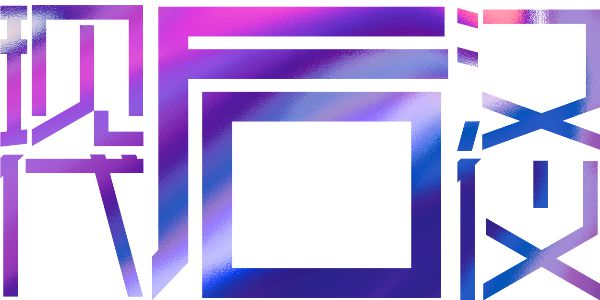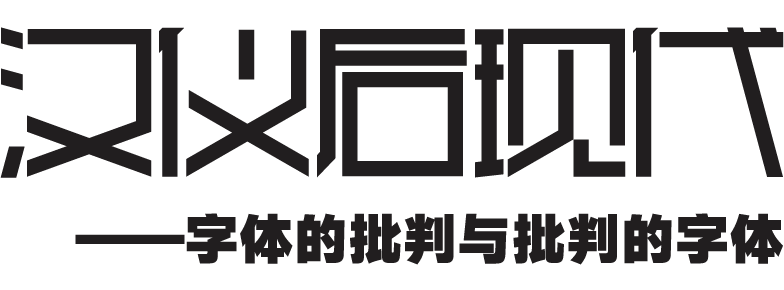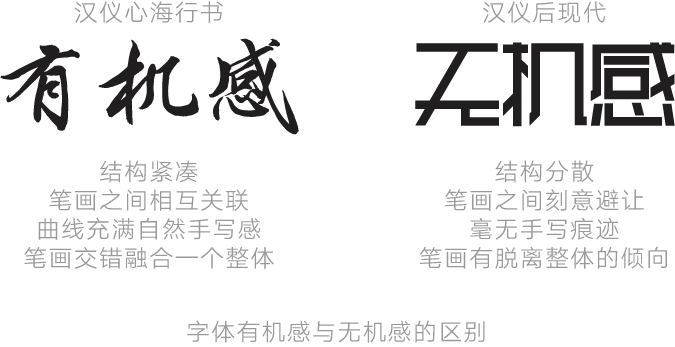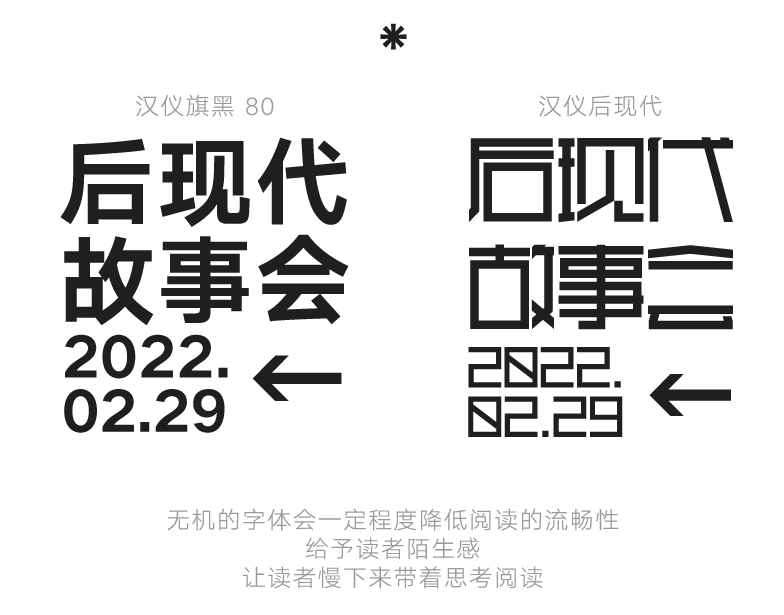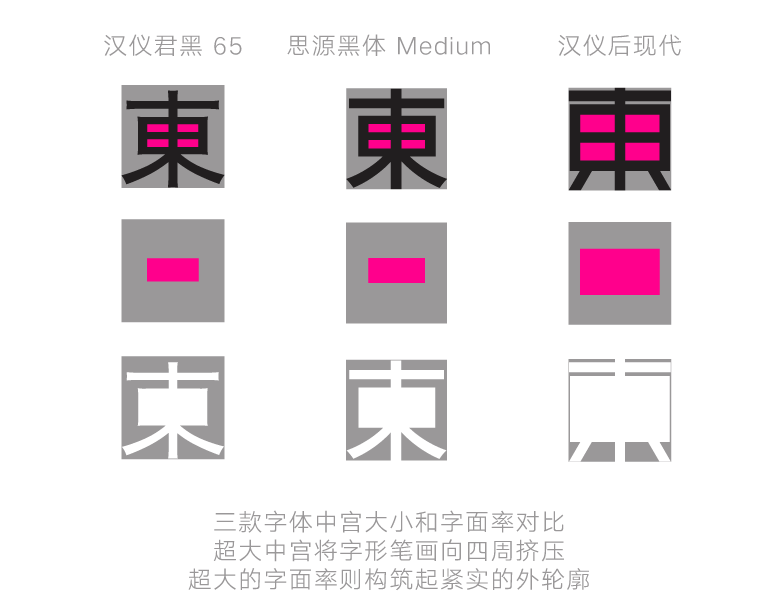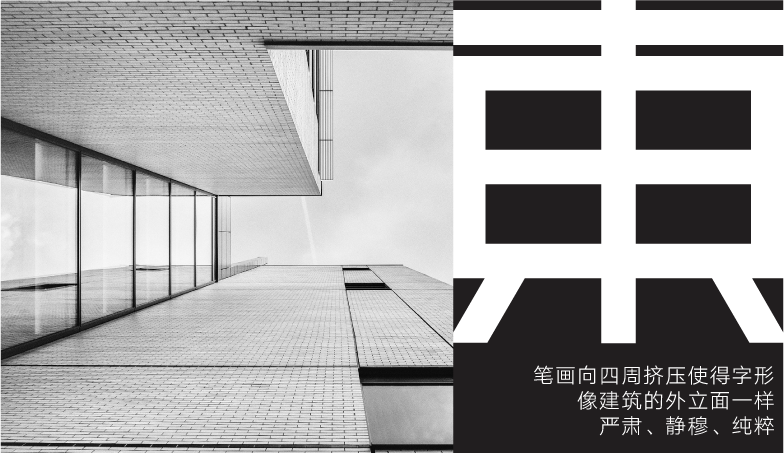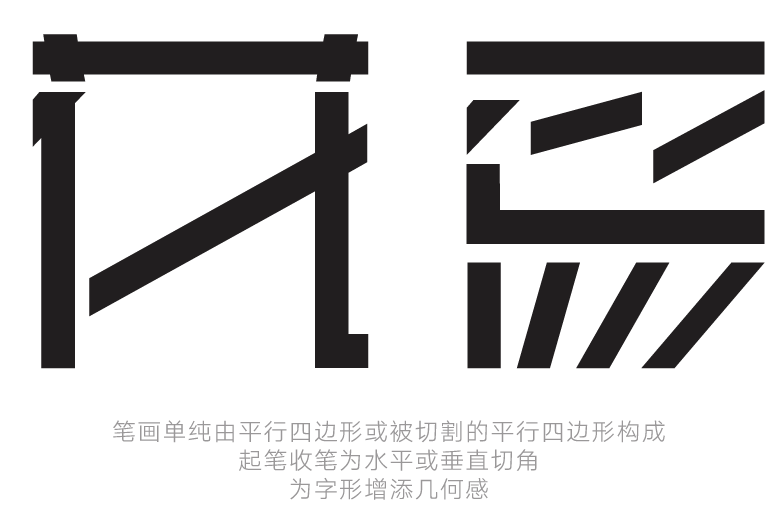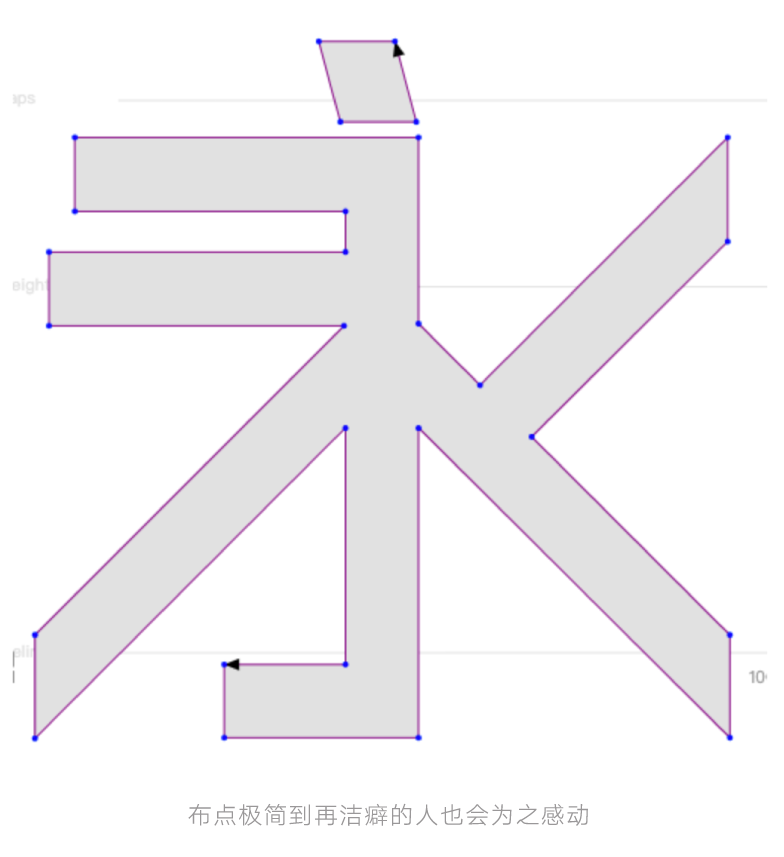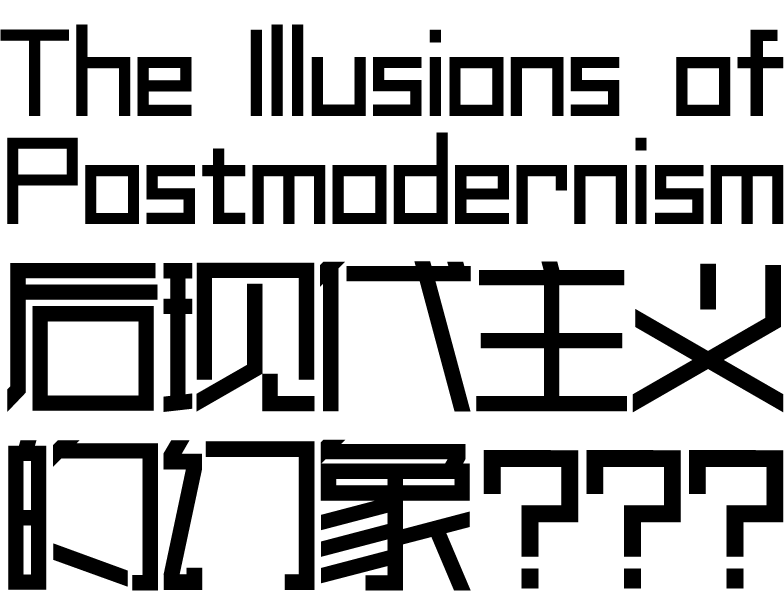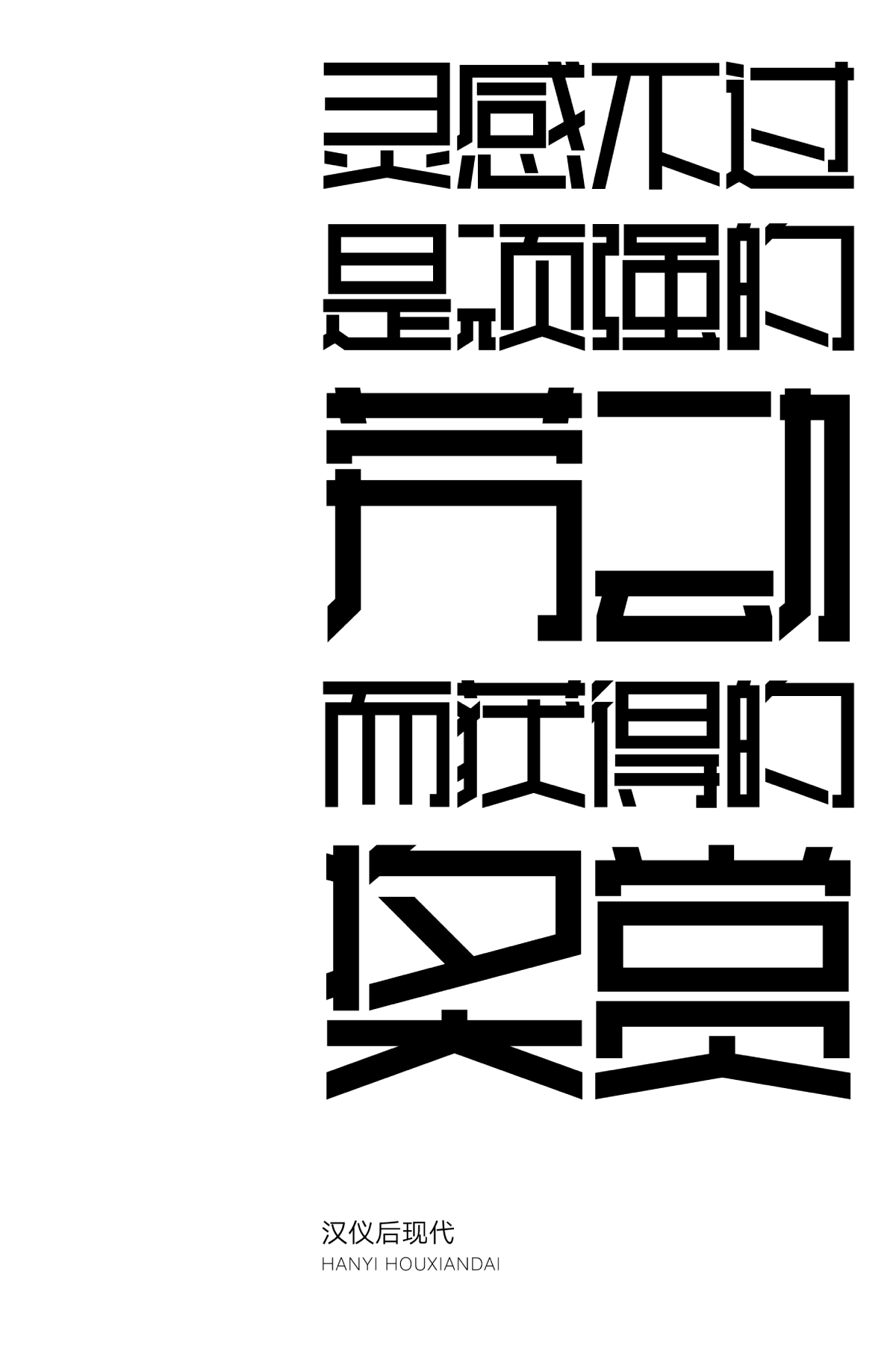
汉仪后现代
后现代 / 时尚 / 简约 / 力量
汉仪后现代是由汉仪签约字体设计师刘痕设计的一款颠覆字形传统设计理念的实验字体。这款字体剥离了汉字笔画之间的有机关系,以一种超大中宫的几何化形态呈现在大众面前。这款字体对传统字形结构进行了批判性颠覆,体现了作者对字体设计理念的思考。但字形依旧遵守了通用规范汉字表的书写规范,保留了一定的规范性与可识别度。
这款字体适合作为标题字,在展会现场、产品包装、广告宣传等需要展现后现代主义风格的场景下使用。
汉仪后现代以超大中宫的形态,剥离了笔画之间的有机关联,让字形呈现出一种陌生感。读者需要花上数秒钟熟悉这款字的结构,才能够正常识读。
这也是这款字体的设计理念所在:并非所有的场合都需要文字被快速流畅地识读。当你需要让读者停下来,让读者去认真思考、体验后续的故事或活动的时候,这款字或许是一个不错的选择。
汉仪后现代的笔画全部由毫无装饰的直线构成。超大的中宫使得字形在视觉上撑满整个字面框,并且将笔画集中在字形四周摆放,这就使得字形的轮廓看起来像建筑的外立面一样,严肃、静穆、纯粹、质朴。
超大的中宫也凸显出字形内部的白空间。由笔画交错切割出来一块块白空间,像建筑上的窗户一样,清澈、透亮。
汉仪后现代笔画粗细均衡统一,略粗的笔画给字形带来一定的厚重感。使得每个字的笔画看起来就像建筑中的一根根骨架,给人一种无表情、无个性的框架感。
汉仪后现代的西文也充满了几何特征,笔画全部由直线构成。相比于建筑般纯粹质朴的汉字设计,这款字体的西文设计更具未来感与科技感。中西文匹配和谐统一。